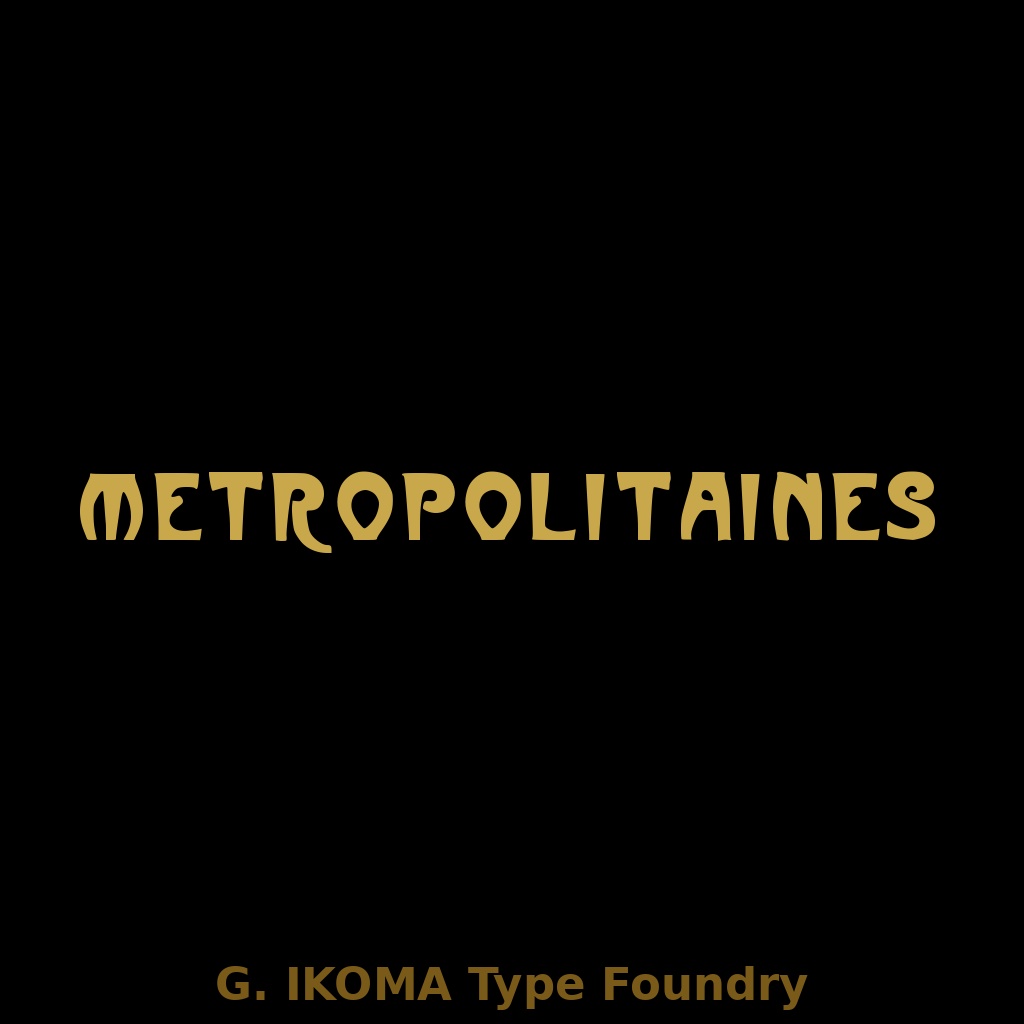
MÉTROPOLITAINES — 19世紀欧州印刷資料復元フォント / Historical Revival Typeface [Art Nouveau Display]
━━━━━━━━━━━━━━━━━━━━━━━━━ 【フォントについて】 ━━━━━━━━━━━━━━━━━━━━━━━━━ **MÉTROPOLITAINES** は、19世紀末〜20世紀初頭の欧州印刷資料を原典に、手作業でトレース・デジタル化した復元フォントです。 本作は、パリの活字鋳造所 **Schriftgiesserei Berthier & Durey** による Art Nouveau 系ディスプレイ書体をもとに再構成したものです。原典資料上部には **「MÉTROPOLITAINES · SCHRIFTGIESSEREI BERTHIER & DUREY, PARIS.」** と記されています。 丸みを帯びた力強い字形と、有機的な曲線を備えたフォルムが特徴で、パリ・アールヌーヴォーらしい装飾性を強く感じさせる書体です。 **原典**:Ludwig Petzendorfer, *Schriften-Atlas* Julius Hoffmann, Stuttgart, 1898(パブリックドメイン) **様式**:Art Nouveau / Display **収録文字**:大文字 A–Z、数字 0–9、記号類 **欠落文字**:小文字 a–z(原典に収録なし) **制作**:株式会社生駒時計店 / G. IKOMA, LTD.(1870年創業) ━━━━━━━━━━━━━━━━━━━━━━━━━ 【ご購入前にご確認ください】 ━━━━━━━━━━━━━━━━━━━━━━━━━ 原典資料に小文字(a–z)の収録がないため、本フォントにも小文字は含まれていません。 そのため、**全大文字組み・頭文字・イニシャル・数字を含む見出し用途** に適しています。 本文組版や、小文字を前提とした通常の欧文組版には向きません。 ━━━━━━━━━━━━━━━━━━━━━━━━━ 【収録内容】 ━━━━━━━━━━━━━━━━━━━━━━━━━ ・MÉTROPOLITAINES.ttf ・LICENSE.txt ━━━━━━━━━━━━━━━━━━━━━━━━━ 【推奨用途】 ━━━━━━━━━━━━━━━━━━━━━━━━━ ・ロゴ ・見出し ・ポスター ・サイネージ ・イベントタイトル ・装丁 ・ラベル ・バナー画像 ・サムネイル画像 **全大文字を活かすディスプレイ用途** に向いています。 本文組版、小文字混在の文章用途には向きません。 ━━━━━━━━━━━━━━━━━━━━━━━━━ 【ライセンス】 ━━━━━━━━━━━━━━━━━━━━━━━━━ 本フォントは、**個人利用・商用利用を問わず**、印刷物、画像、ロゴ、バナー、動画サムネイル等の制作に使用できます。 また、**WebサイトやSNSで画像化された状態で使用することは可能**です。 ただし、以下の行為は禁止します。 ・フォントファイルそのものの再配布、再販売、譲渡、共有 ・改変したフォントファイルの配布 ・本フォントを素材集、テンプレート、デジタル商品等に収録して再販売する行為 ・**本フォントファイルをWebフォントとしてサーバーに設置・配信して利用する行為** ・アプリケーション、ゲーム、ソフトウェア、電子機器等への埋め込み利用 ・AI学習、機械学習、生成モデル訓練等への利用 ・本フォント自体または収録字形そのものについて独占的権利を主張する行為 詳細は同梱の **LICENSE.txt** をご確認ください。 ━━━━━━━━━━━━━━━━━━━━━━━━━ 【原典資料について】 ━━━━━━━━━━━━━━━━━━━━━━━━━ 本フォントは、G. IKOMA, LTD. 所蔵の実物資料をもとに制作しています。 原典資料そのものは本商品に含まれていません。 資料アーカイブについては、下記サイトをご参照ください。 G. IKOMA Archive [https://g-ikoma-archive.netlify.app/](https://g-ikoma-archive.netlify.app/)